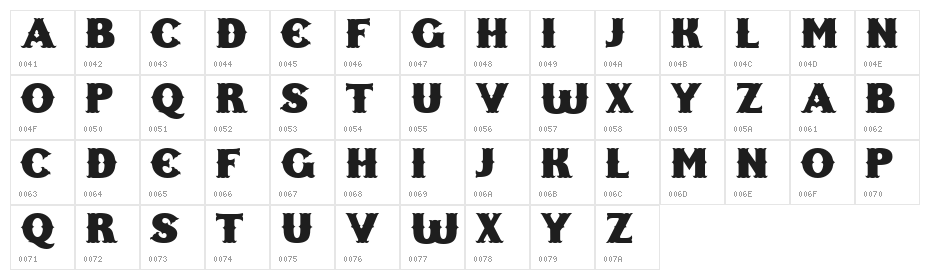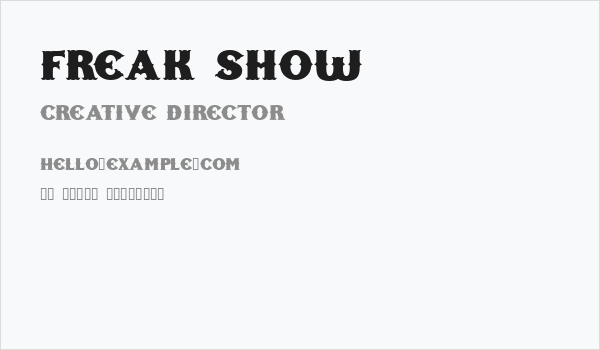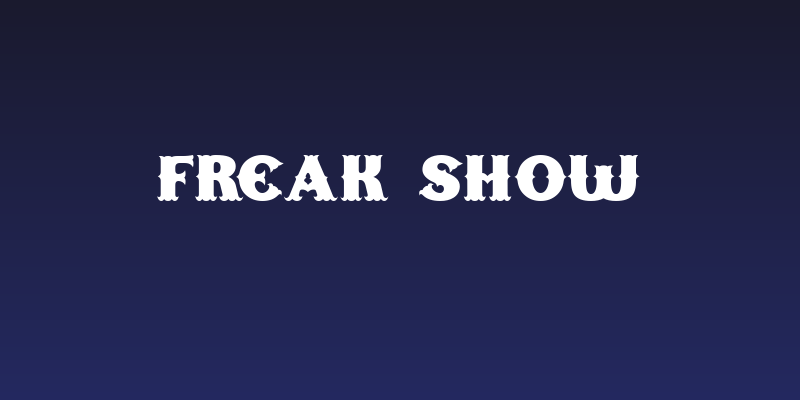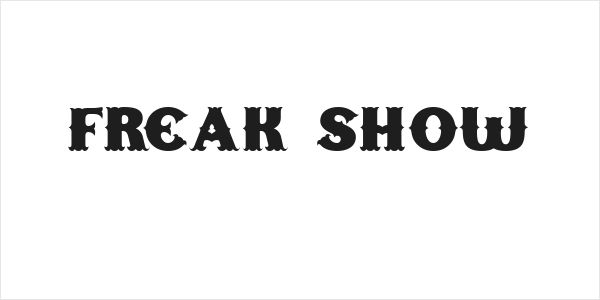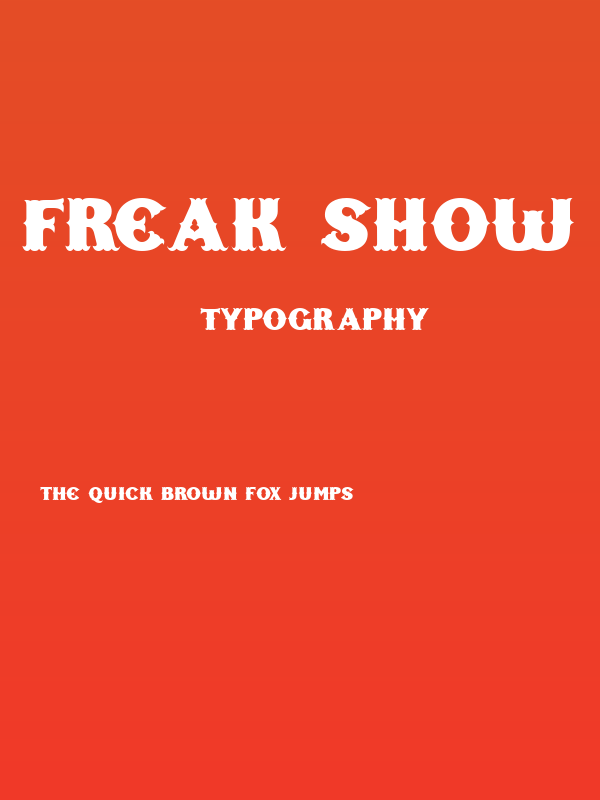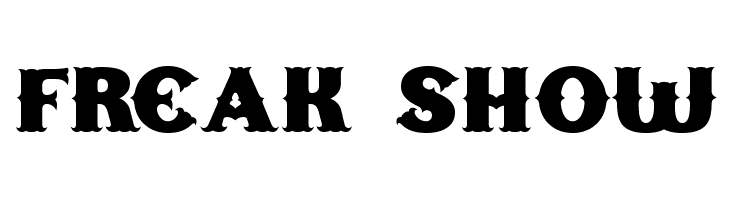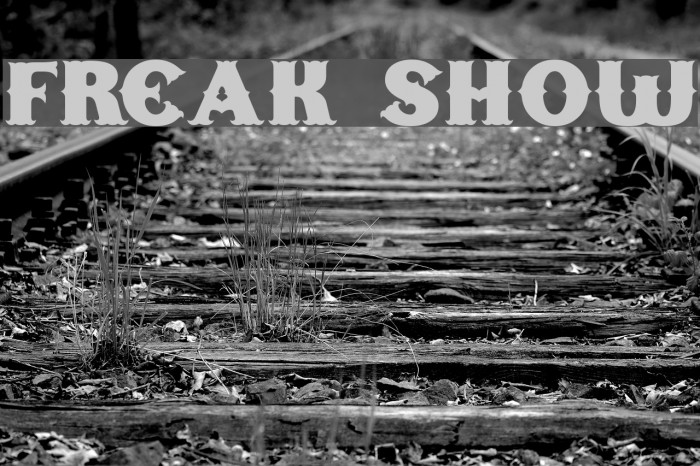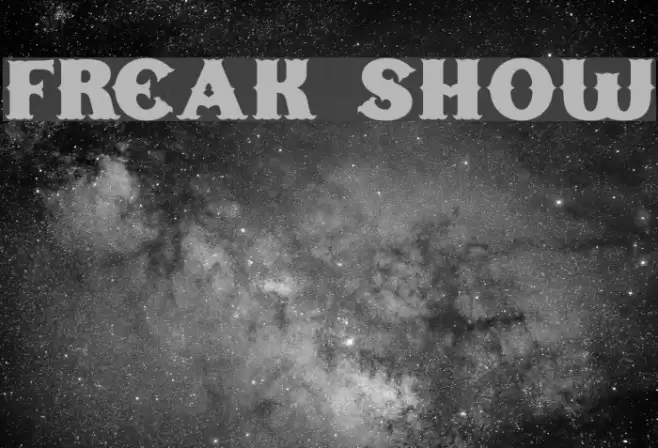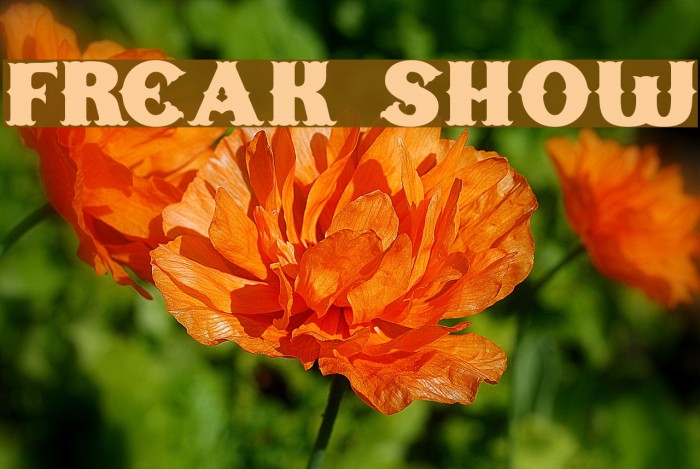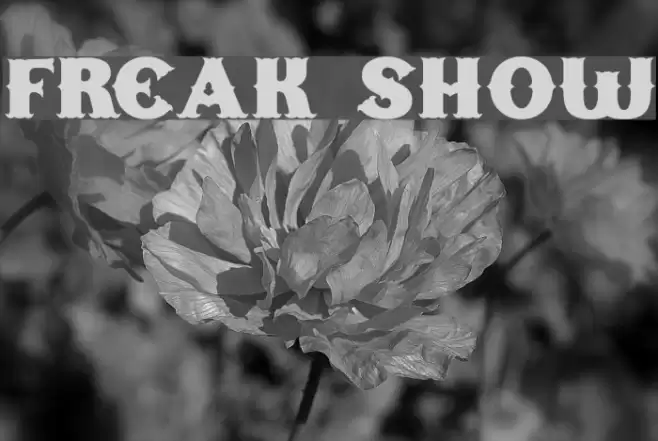
Freak Show Font
| النمط العام | Vintage |
| مشاريع مقترحة | Ideal for vintage-themed posters, circus or fairground signage, theatrical event invitations, or any project needing a nostalgic touch. |